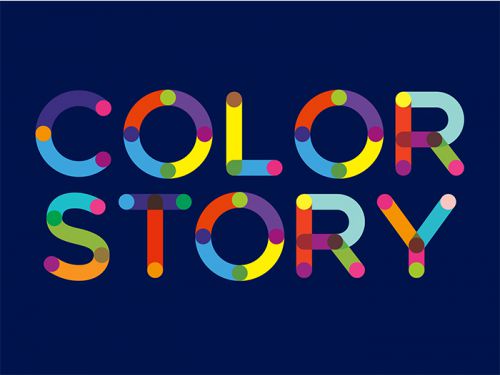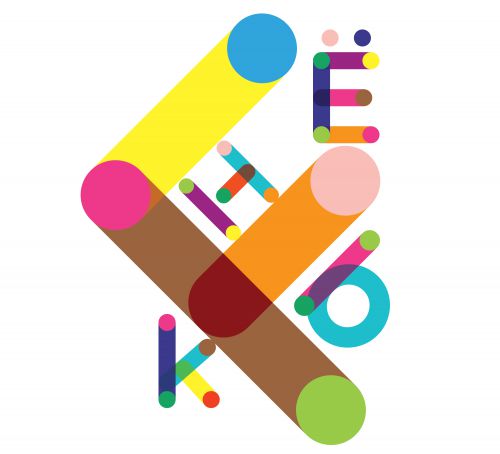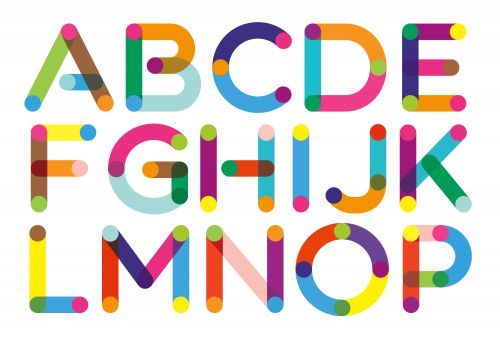
ColorTube
ColorTube是一款专为创意设计打造的英文Display彩色字体,以可爱有趣的风格著称,适合为各类视觉作品注入灵动活力。 ColorTube的字形设计兼具细节巧思与实用价值:修长的字体结构搭配居中重心,中宫适中的比例让字符在保持优雅感的同时,具备良好的阅读流畅度。笔画采用圆润端头与斜切处理,粗细均匀的线条搭配局部断开的连接设计,既保留了可爱俏皮的视觉张力,又通过结构平衡避免了杂乱感——圆头笔画增添软萌气质,斜切细节则注入一丝利落个性,让每个字母都如同“彩色小管”般鲜活有趣。 作为支持免费商用授权的字体,ColorTube覆盖常规英文(拉丁)字符集,能满足海报设计、社交媒体配图、品牌年轻化视觉等多元场景需求。其自带的彩色属性无需额外调色,即可直接呈现鲜明色彩表现力,无论是打造趣味标题还是活泼图标,都能快速抓住观者眼球。 无论是制作活泼的社交媒体内容、趣味主题海报,还是设计年轻化品牌LOGO,ColorTube都能凭借独特的字形语言与色彩优势,让创意设计既亮眼又富有记忆点,成为免费商用字体中兼具颜值与实用性的优选。